Tính năng OpenType là một phần không thể thiếu trong thiết kế và sử dụng font chữ hiện đại. Đây là công nghệ font chữ tiên tiến, với sự hỗ trợ rộng rãi cho các ngôn ngữ và ký tự đặc biệt, cùng với khả năng tùy chỉnh cao. OpenType đã mở ra một kỷ nguyên mới trong việc biểu đạt văn bản và thiết kế chữ viết.
Với OpenType, người dùng có thể truy cập vào các glyph thay thế, ligature, các chữ số, và nhiều tính năng khác để tạo ra văn bản đẹp mắt và chuyên nghiệp hơn.
OpenType là gì?
OpenType (OTF) là định dạng phông chữ được Adobe và Microsoft cùng phát triển vào cuối những năm 1990. Nó chỉ được sử dụng rộng rãi hơn sau năm 2000, khi Adobe hỗ trợ các tính năng typographic nâng cao trong các ứng dụng Photoshop, Illustrator và InDesign của họ.
Phông chữ OpenType hỗ trợ Unicode, có nghĩa là một phông chữ OpenType có chứa hơn 65.000 glyph. Một phông chữ duy nhất có thể được sử dụng để cài đặt văn bản bằng nhiều ngôn ngữ khác nhau. Ngoài ra, phông chữ OpenType hỗ trợ đa nền tảng cùng một tệp có thể được sử dụng trên Mac và PC, thậm chí sử dụng được cả trên web.
Không phải tất cả các phông chữ OpenType đều chứa hàng nghìn ký tự. Trên thực tế, hầu hết các phông chữ OpenType đều là phông chữ PostScript được chuyển đổi chỉ chứa 256 glyph.
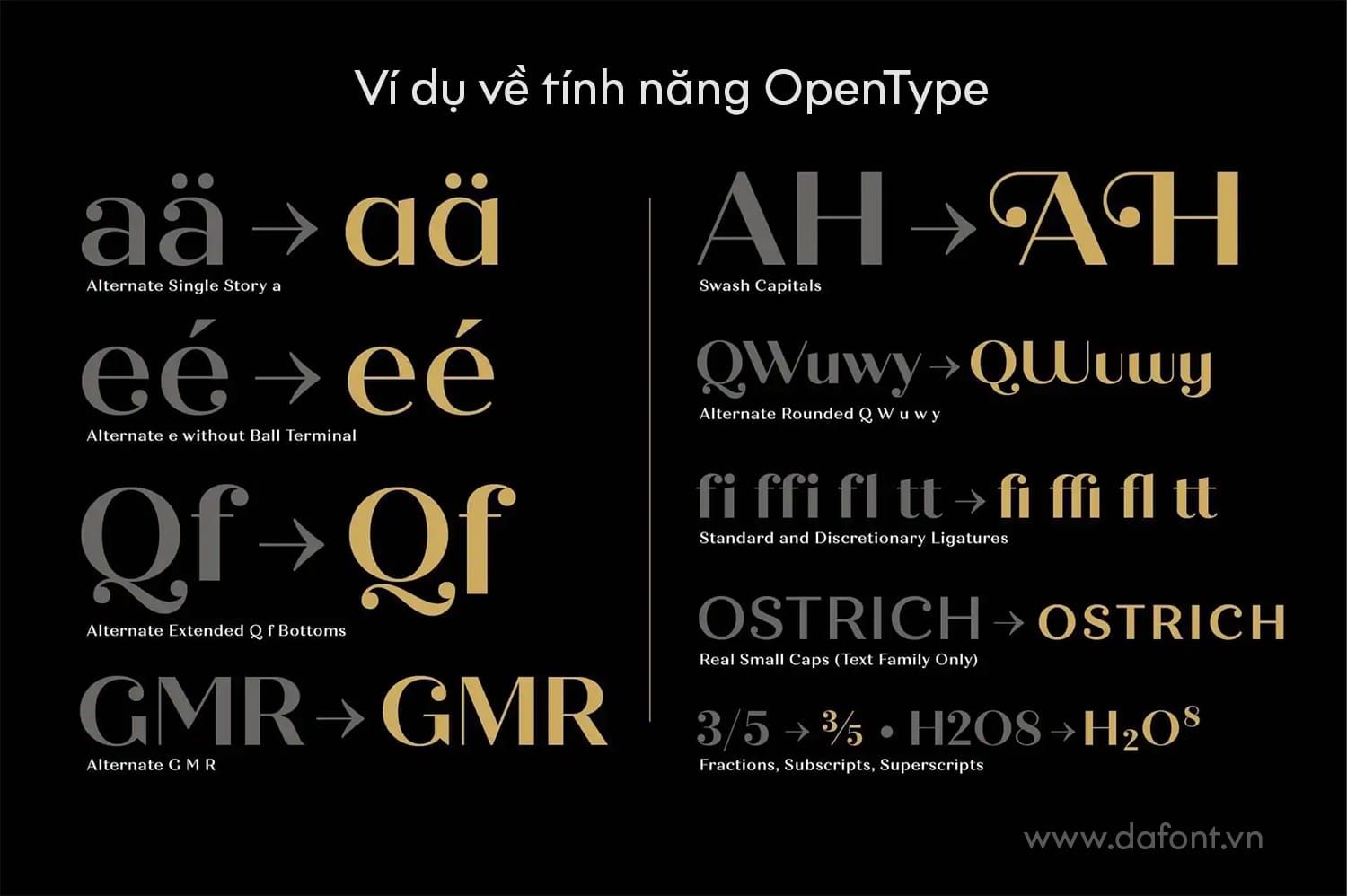
Font OpenType bao gồm các bộ ký tự và tính năng bố cục được mở rộng rộng rãi, cung cấp hỗ trợ ngôn ngữ phong phú hơn và kiểm soát kiểu chữ nâng cao. Bạn có thể bật các tính năng OpenType tự động thay thế các ký tự thay thế trong phông chữ OpenType, như các stylistic alternates, contextual alternates, small caps, style sets, và swashes.
Cách truy cập tính năng của OpenType
Hầu hết các ứng dụng Mac và Windows đều tương thích với OpenType. Trong các ứng dụng như Photoshop, Illustrator và InDesign, chỉ cần chọn menu OpenType trên bảng Character. Ngoài ra, bất kỳ glyph thay thế nào trong phông chữ OpenType đều có thể được chọn thủ công thông qua bảng Glyph.
Định dạng
Phông chữ OpenType có thể được cài đặt và sử dụng cùng với phông chữ PostScript Type 1 và TrueType. Phông chữ OpenType chứa dữ liệu PostScript có hậu tố .otf trong tên tệp phông chữ, trong khi phông chữ OpenType dựa trên TrueType có hậu tố tên tệp .ttf. Để biết thêm thông tin về định dạng OpenType thực tế, bạn có thể xem thêm tại trang của Adobe.
Tương lai của OpenType
OpenType tiếp tục được cải tiến và cập nhật để đáp ứng nhu cầu ngày càng cao của các nhà thiết kế và người dùng cuối. Việc phát triển các tính năng mới và hỗ trợ thêm nhiều ngôn ngữ và ký tự vẫn đang diễn ra.
Nhờ vào sự linh hoạt và sức mạnh của mình, OpenType đã trở thành chuẩn phông chữ thống trị trong ngành công nghiệp sáng tạo và công nghệ thông tin.